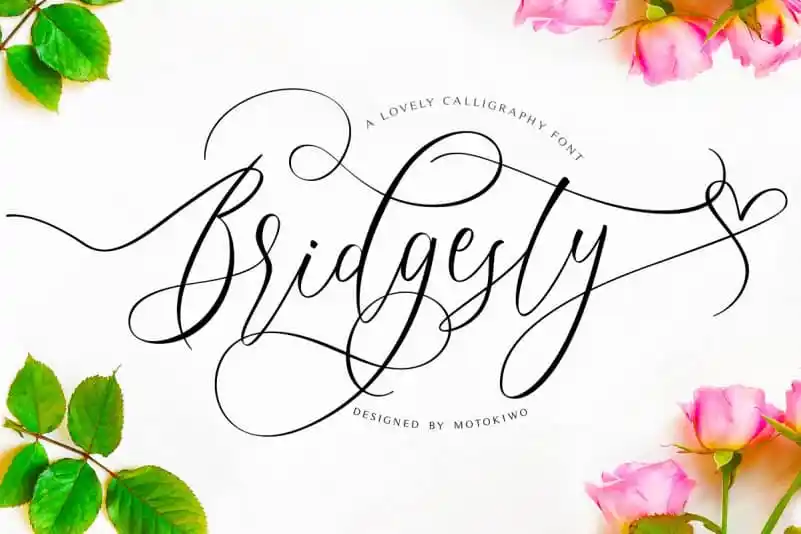
Bridgesty Script Font – Fonte Grátis
Bridgesty Script Font
A Bridgesty Script Font é uma exquisiteza para quem busca um texto atraente e sofisticado. Ela carrega um charme romântico com suas linhas elegantes e arredondadas, perfeita para gráficos de casamento. Desenvolvida pelo designer Motokiwo, esta fonte em estilo calligrafia é uma opção ideal para quem busca algo que seja ao mesmo tempo bonito e versátil. Além disso, a Bridgesty Script Font vem com características adicionais que tornam o seu uso ainda mais impressionante: ligaturas, alternativas contextualizadas, formas inicialísticas e finais, conjuntos estilizados, swashes e suporte para múltiplas línguas. O PUA (Propagandação de Usagem Assíncrona) já está pré-aplicado nessa fonte, o que lhe permite aproveitar suas habilidades completas sem necessidade adicional de configurações. Uma fonte como esta é ideal para quem busca um toque único e sofisticado em seus projetos gráficos.